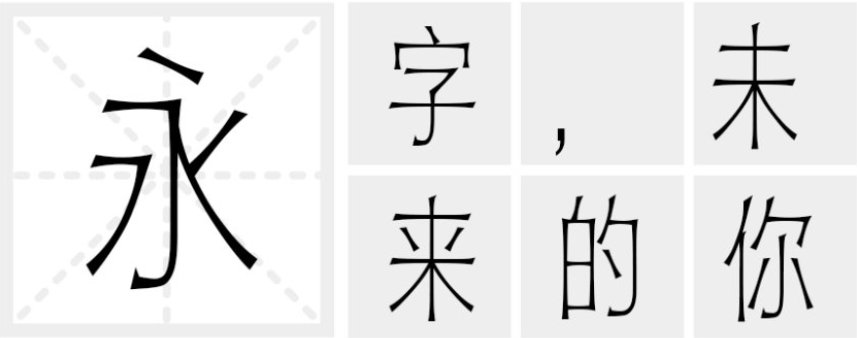
三极竹枝简体字体轻巧简洁,笔画粗细匀称,连接处为竹节状,特点独特。起笔收笔为平直有力,折、钩转折明显如竹之嫩条。
这是一款充满设计感的创意字体它的灵感来源于竹枝形状,字体纤细挺拔,耐人寻味。视觉效果简洁挺拔实用性强。本作品适用于印刷媒介的标题与正文排版、各类屏幕显示及影视字幕、游戏等。
适用场景:影视字幕、游戏